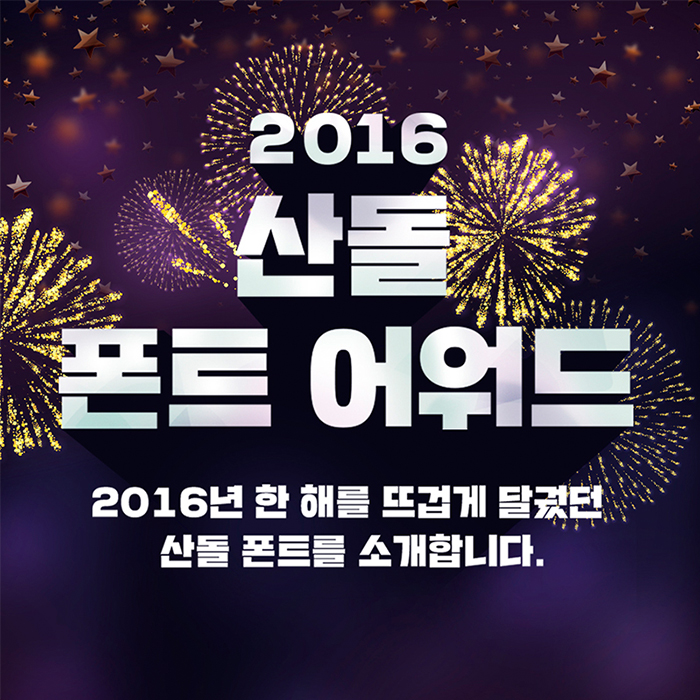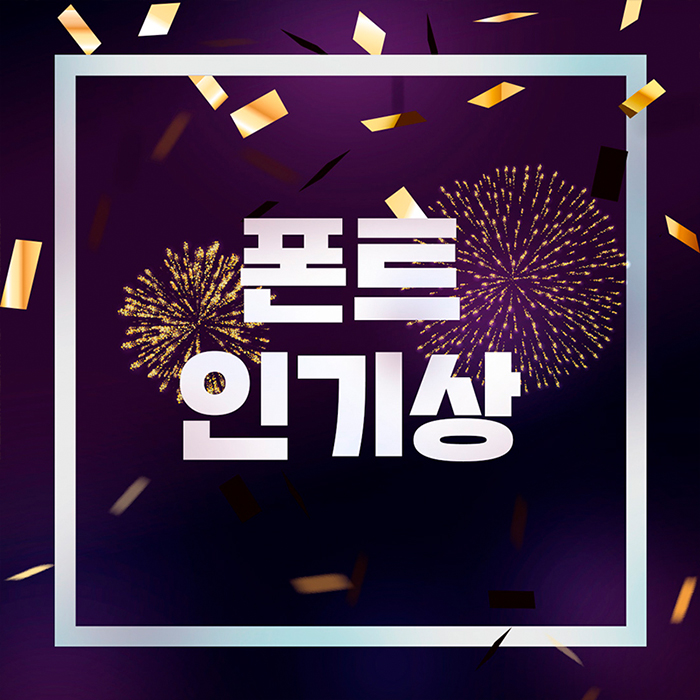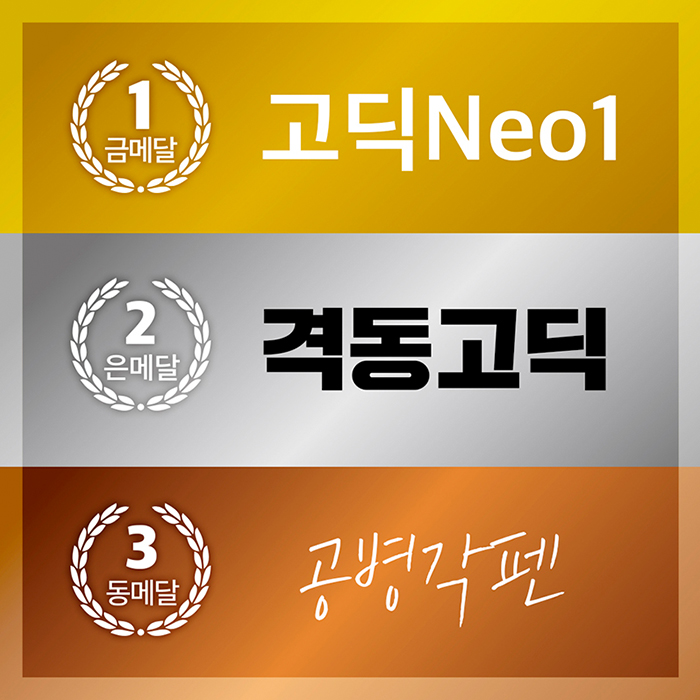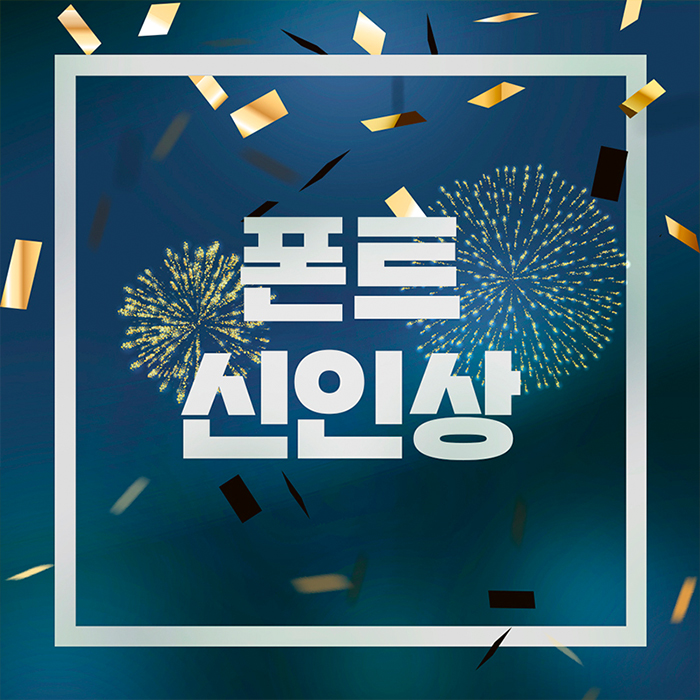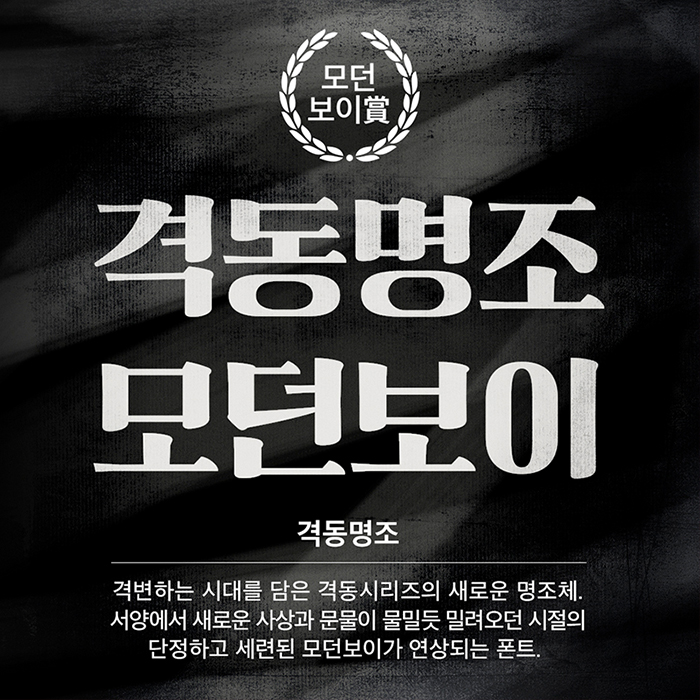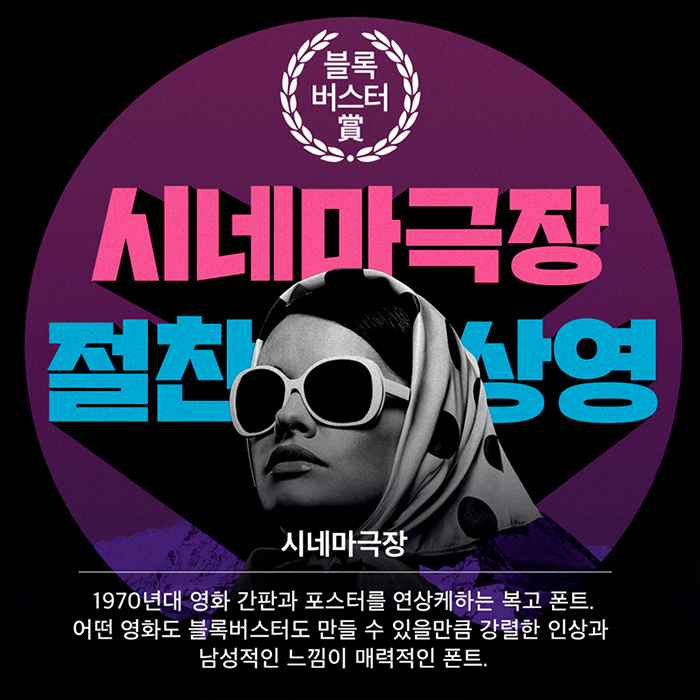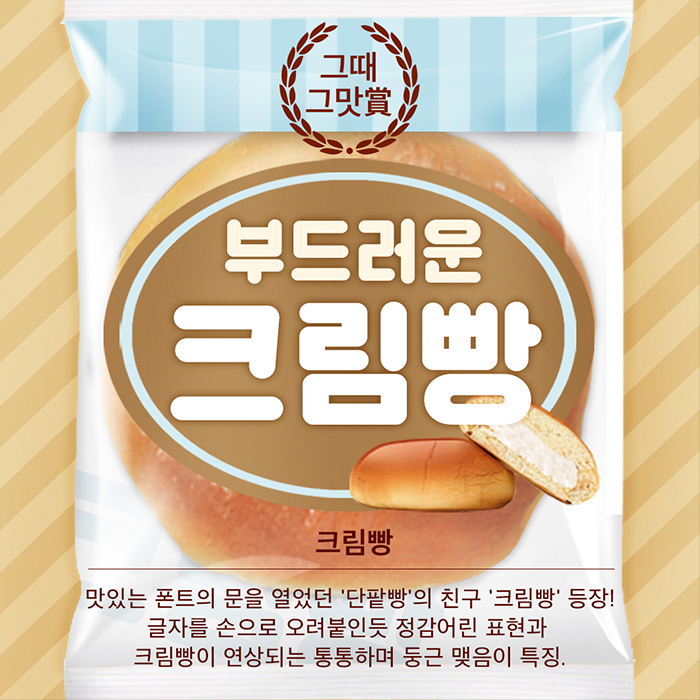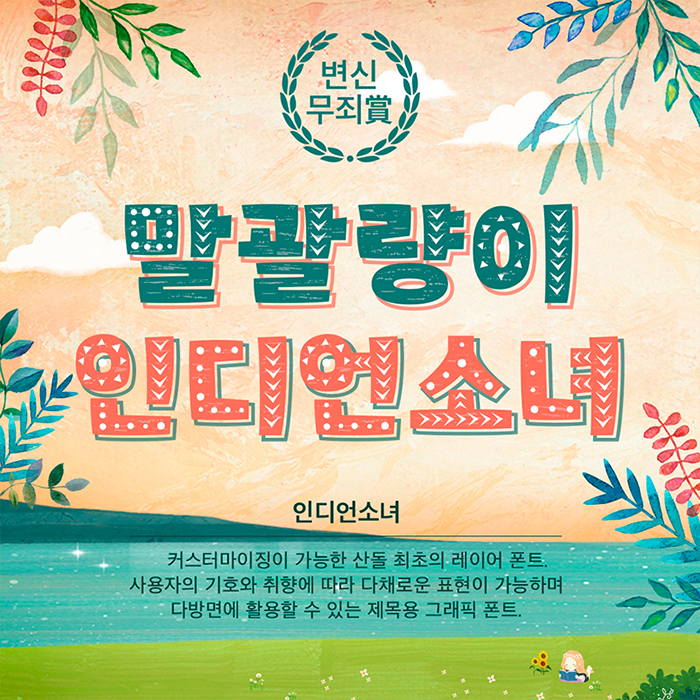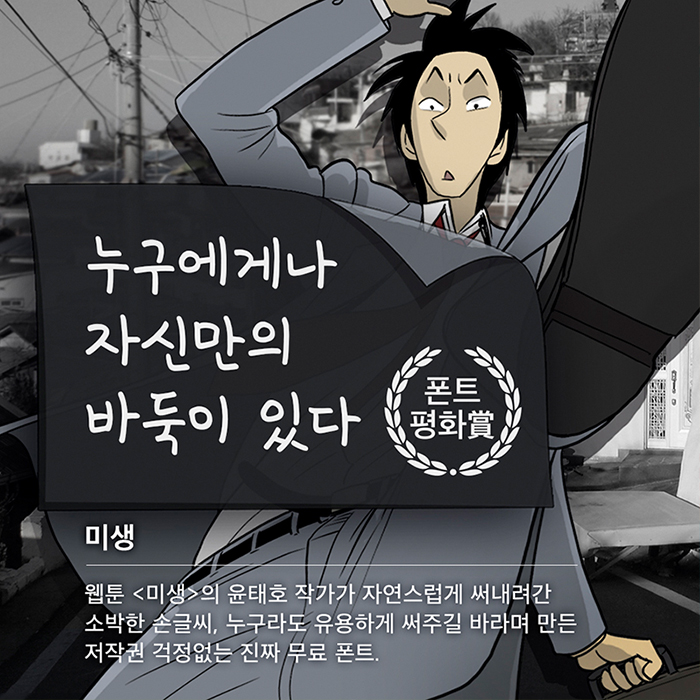
산돌 폰트 어워드 : 2016년 당신이 사랑한 폰트!
2016년 한 해 동안, 당신이 가장 사랑한 폰트는 무엇인가요?
산돌이 만든 500여 종의 폰트 중에서 2016년에 가장 많이 사랑받았던 폰트!
이른바, 산돌 폰트 어워드 2016, 그 영광의 수상작들을 만나보시죠.
산돌 폰트 어워드 2016
2016 폰트인기상
2016년, 가장 많은 사랑을 받았던 최고의 인기폰트는 고딕Neo1이었습니다.
출시 이후부터 지금까지, 언제나 꾸준하게 사랑받는 산돌의 대표적인 프리미엄 본문 폰트!
2위는 작년에 큰 사랑을 받았던 격동고딕이며, 3위는 공병각펜이 차지했습니다.
폰트 신인상
2016년에 출시된 폰트 중에서는 미생이 가장 많은 사랑을 받았습니다.
완전 무료폰트로 저작권 걱정이 없어서 더욱 많은 사랑을 받은 것 같습니다.
2위는 강한 임팩트의 소유자 시네마극장이며, 3위는 감성명조 늦봄이 차지했습니다.
모던보이賞 – 격동명조
격변하는 시대를 담은 격동시리즈의 새로운 명조체, 격동명조
서양에서 새로운 사상과 문물이 물밀듯 밀려오던 시절의 단정하고 세련된 모던보이가 연상되는 폰트
블록버스터賞 – 시네마극장
1970년대 영화 간판과 포스트럴 연상케하는 복고 폰트, 시네마극장
어떤 영화도 블록버스터로 만들 수 있을만큼 강렬한 인상과 남성적인 느낌이 매력적인 폰트
그 때 그 맛賞 – 크림빵
맛있는 폰트의 문의 열었던 ‘단팥빵’ 친구 ‘크림빵‘
글자를 손으로 오려붙인듯 정감어린 표현과 크림빵이 연상되는 통통하며 둥근 맺음이 특징
변신무죄賞 – 인디언소녀
커스터마이징이 가능한 산돌 최초의 레이어 폰트, 인디언소녀
사용자의 기호와 취향에 따라 다채로운 표현이 가능하며 다방면에 활용할 수 있는 제목용 그래픽 폰트
폰트평화賞 – 미생
웹툰 <미생>의 윤태호 작가가 자연스럽게 써내려간 소박한 손글씨, 미생
누구라도 유용하게 써주길 바라며 만든 저작권 걱정없는 진짜 무료 폰트
문학소녀賞 – 늦봄
붓글씨 특유의 느낌을 담은 새로운 감성 명조체, 늦봄
서정적인 아름다움이 느껴지는 부드러운 형태가 특징
전문가 인정賞 – 나눔스퀘어
한국 대표 포털 네이버와 한글 대표 산돌이 함께 만든 무료폰트, 나눔스퀘어
2016년 국제 타입 디자인 대회인 Granshan에서 한글부문 1위를 차지!